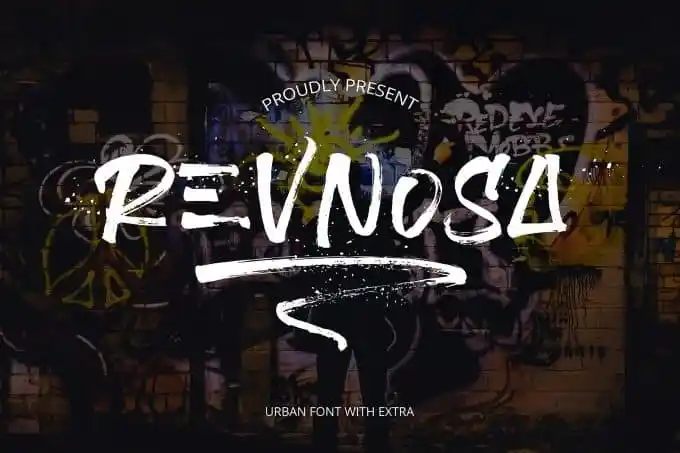
Revnosa Brush Font – Download Grátis
Revnosa Brush Font é uma opção atraente para projetos que buscam destacar-se visualmente com texturas suaves e estilo urbano. Seus traços rápidos e seu aspecto rusticamente charmoso complementam qualquer projeto de headline, tornando-o perfeito para aplicações como texto citado, nomes de produtos, camisetas streetwear, embalagens de produto e muito mais. A fonte foi criada pelo designer PeterDraw à partir de uma mistura de escrita manuscrita ao vivo, combinando elementos urbanos em um design único e elegante. Ideal para projetos visuais que buscam personalidade e originalidade, Revnosa Brush Font se destaca como uma escolha versátil para qualquer aplicação gráfica.